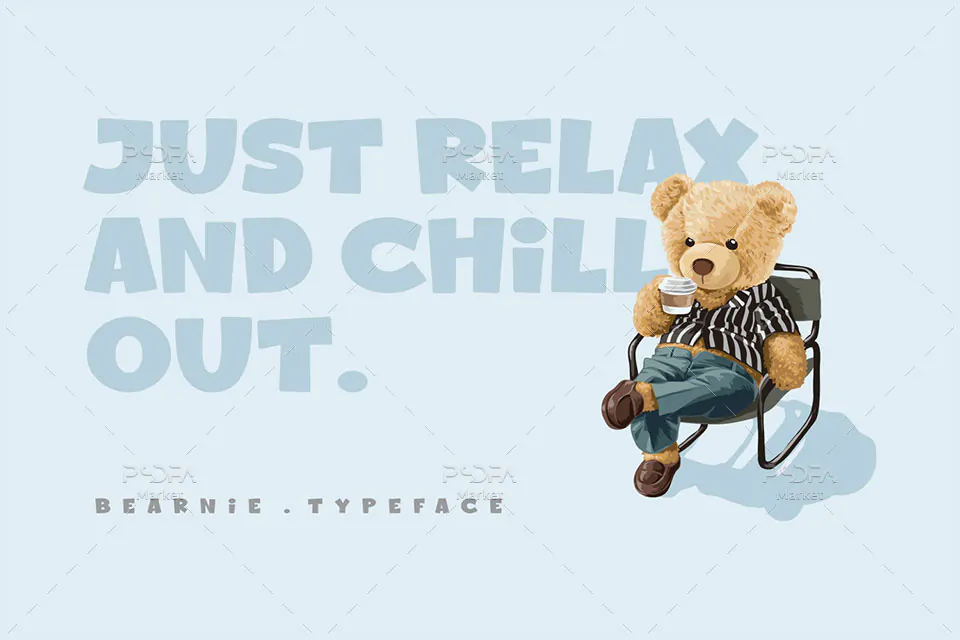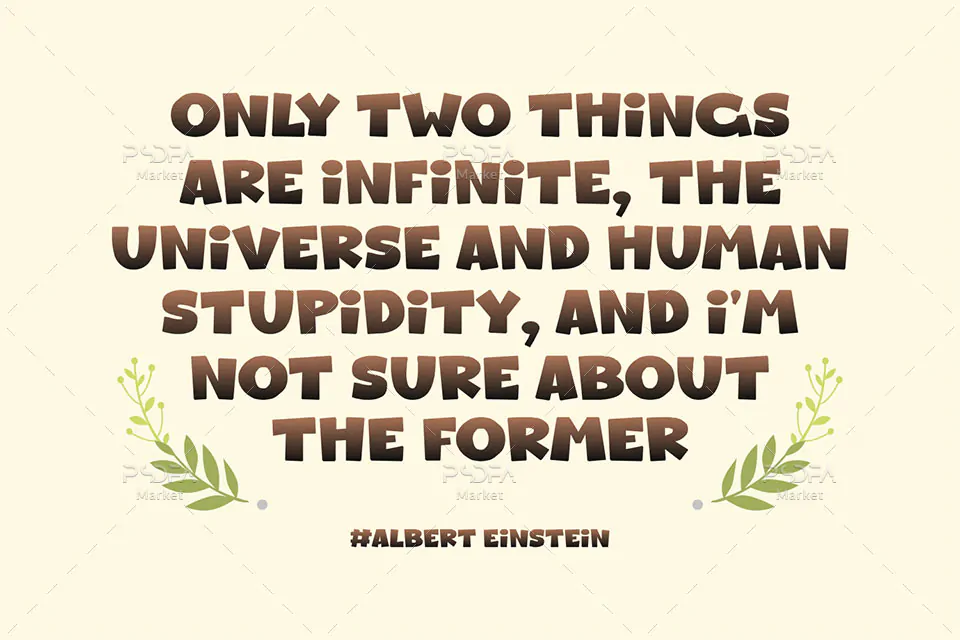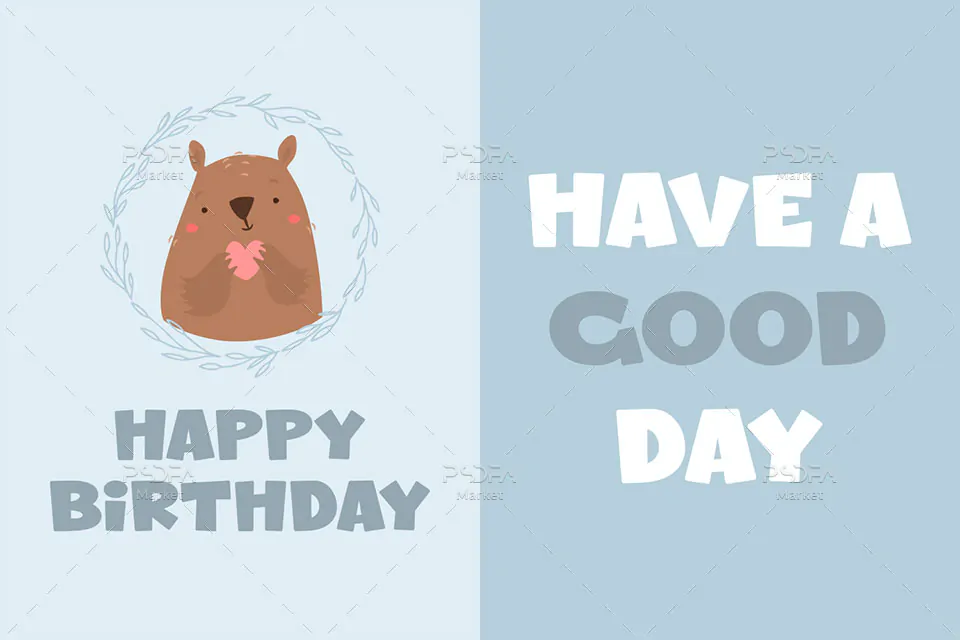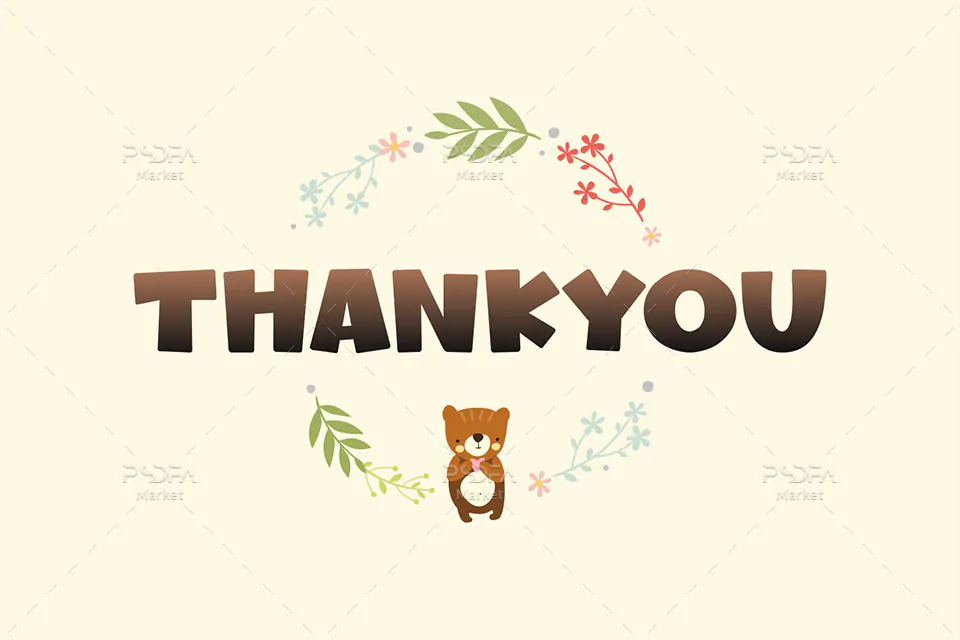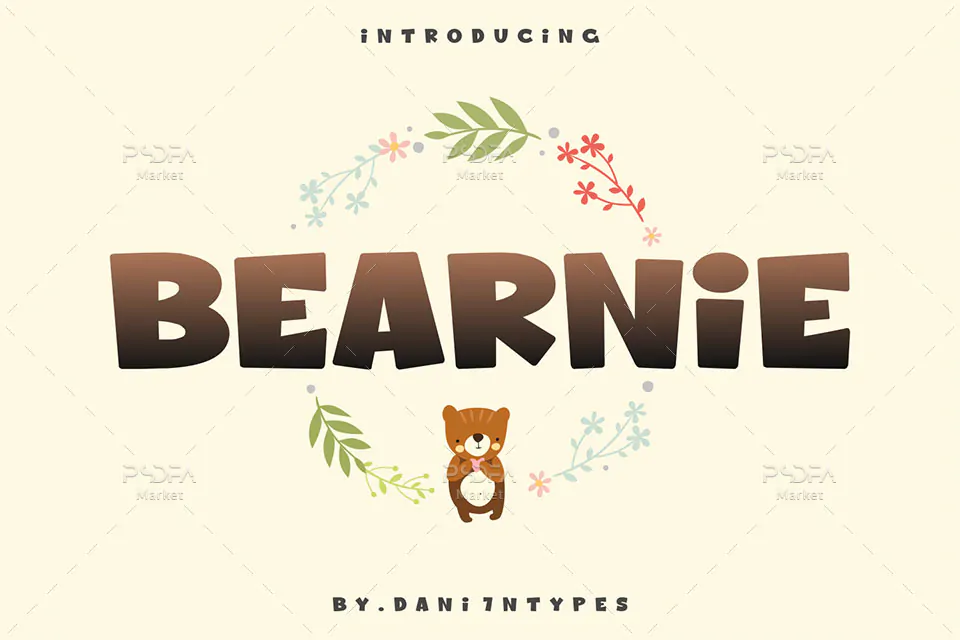
فونت انگلیسی کارتونی و کودکانه Bearnie مناسب برای طراحی
فونت انگلیسی کارتونی و کودکانه Bearnie
فونت انگلیسی کارتونی و کودکانه Bearnie یک قلم زیبا است که مناسب جهت استفاده در طرح و پروژههای گرافیکی مختلف به خصوص طراحی تیتر و عناوین طرحهای کارتونی و کودکانه میباشد. این فونت زیبا در قالب یک فایل OTF در فایل محصول قرار دارد که با نصب آن در پوشه فونتهای سیستم میتوانید از این فونت انگلیسی زیبا در تمام نرم افزارهای گرافیکی و تایپ متون همچون فتوشاپ، افتر افکت، پریمیر، ورد، پاورپوینت و … استفاده کنید.
فونت Bearnie در وزن معمولی (Regular) طراحی شده است که میتوانید از آن در طراحی انواع کارت تبریک، کارت پستال، کارت ویزیت، طراحی انواع بنر، پوستر، تراکت، تقویم و دیگر طرحهای گرافیکی استفاده کنید.